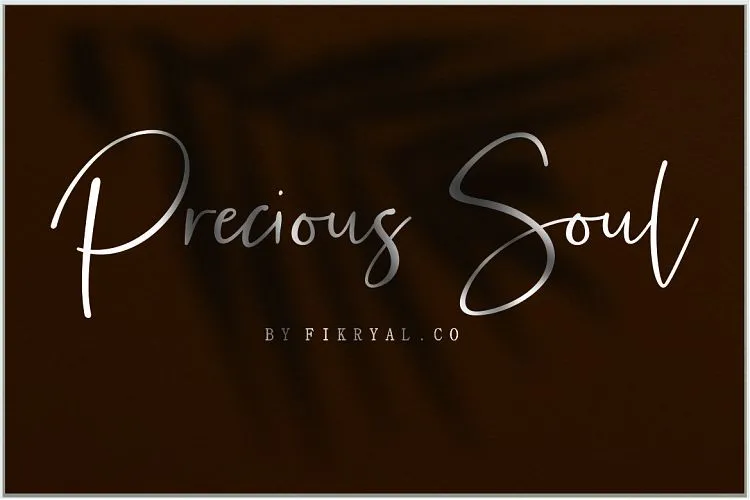
Precious Soul Script Font – Download Grátis
Esta fonte é uma elegante seleção de traços feitos à mão com 236 total glyphs. Fikryal lançou-a especialmente para designs atraentes, como convites e estaçãoários para festas casamentais. A Precious Soul Script Font é um tipo moderno e moderno criado pela designer C00zona. É perfeito para uso em logotipos, identidade de marca, convites, cabeçalhos, designs de casamento, posts nas redes sociais, anúncios, embalagens de produtos, designs dos produtos, etiquetas, fotografia, marcas especiais, revistas, design da web e muito mais. Esta fonte é uma verdadeira jóia para qualquer designer buscando um traço elegante que complementa suas criações visuais com delicadeza e estilo.